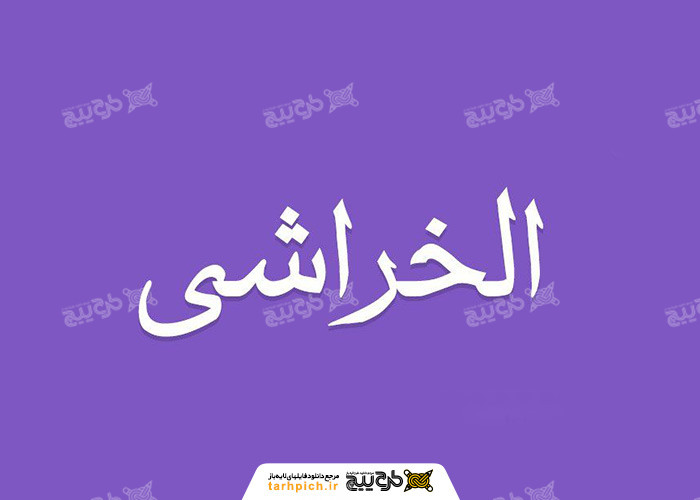
فونت عربی الخاشعی
فونت عربی الخاشعی  با طراحی چشم نوازی و خوانایی بالا   گزینه ای مناسب  برای طراحان و نویسندگانی است که به دنبال زیبایی و اصالت در آثار خود هستند.این فونت در دسته بندی فونت های عربی قرار دارد.اگر به دنبال خرید فونت هستید کافیست روی لینک رنگی کلیک کنید.برای دیدن فونت‌های دیگر می‌توانید به سایت لایه باز طرح پیچ مراجعه کنید